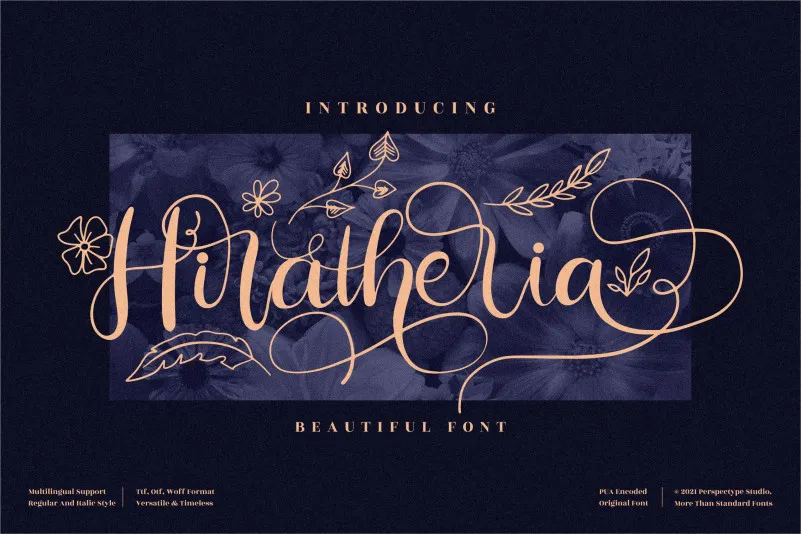
Hiratheria Font – Download Grátis
Aqui está uma descrição em português do Brasil para a página de download da fonte ‘Hiratheria Font’, mantendo os critérios fornecidos: Esta fonte é um verdadeiro prazer ao olhar e manipular, caracterizada por seu acabamento meticuloso e detalhado. Seja você designer gráfico, fotógrafo ou ilustrador, esta font vai ser uma invaluable adição à sua biblioteca de fontes. Com seu potencial para enriquecer quaisquer criações, ‘Hiratheria Font’ é uma escolha perfeita para estilos de script e escrita fluida. Além disso, a fonte conta com PUA (Propriedade Unicode Álbuns) encodadas, o que lhe permite acessar facilmente todos os símbolos e desenhos alternativos sem qualquer dificuldade. É uma ótima opção para quem deseja adicionar um toque único e sofisticado a seus projetos digitais. Hiratheria é uma fonte que não apenas oferece beleza visual, mas também flexibilidade. Suas características detalhadas permitem que você personalize suas criações de maneira única sem limitações. Com uma variedade de símbolos e desenhos alternativos, essa fonte será um aliado valioso para quem busca expressar sua criatividade de maneira fluida e elegante.